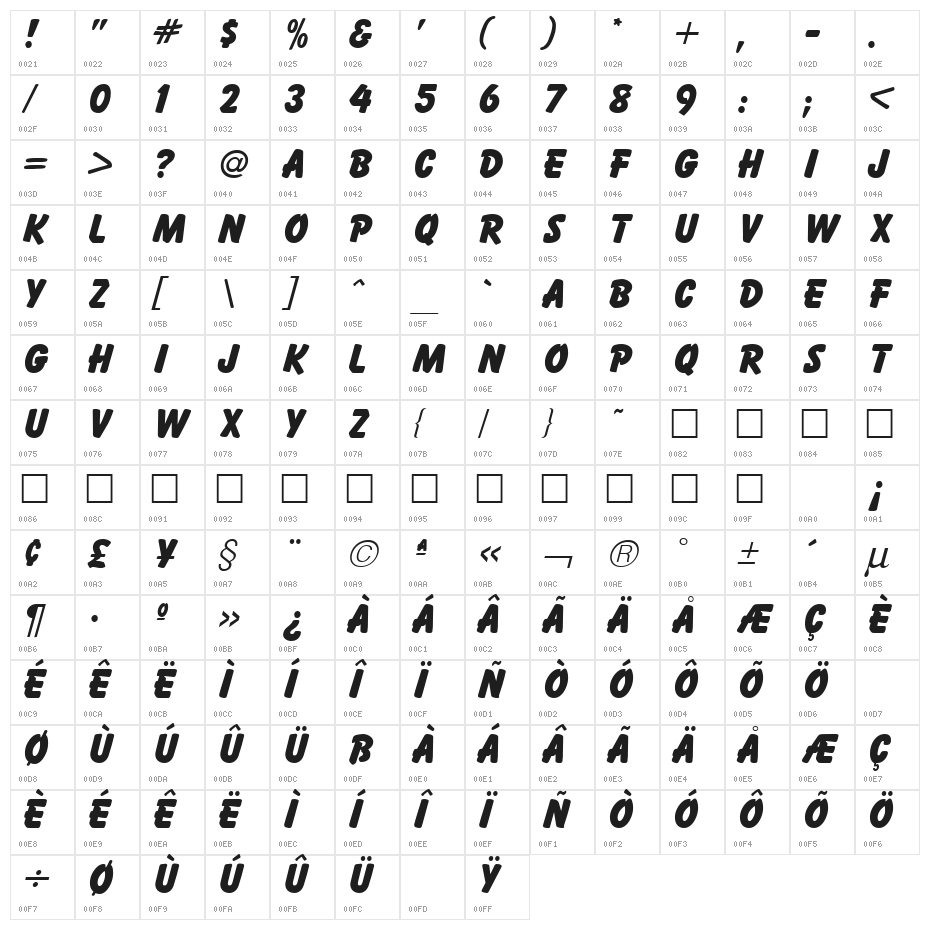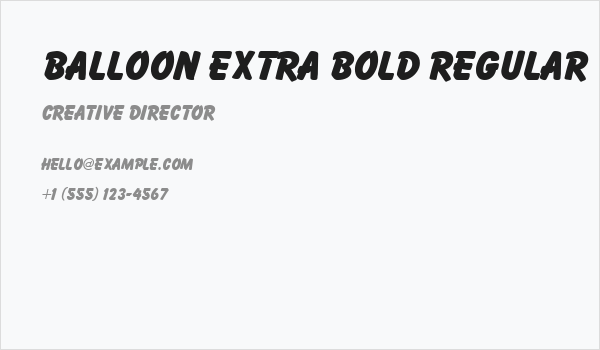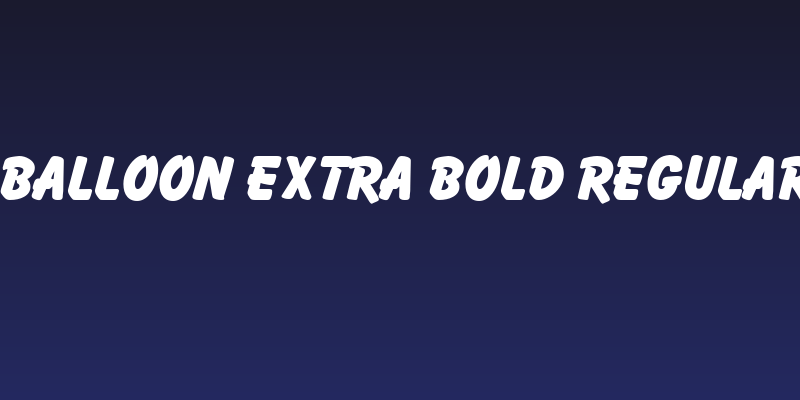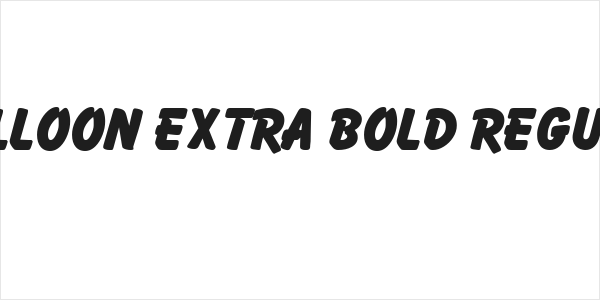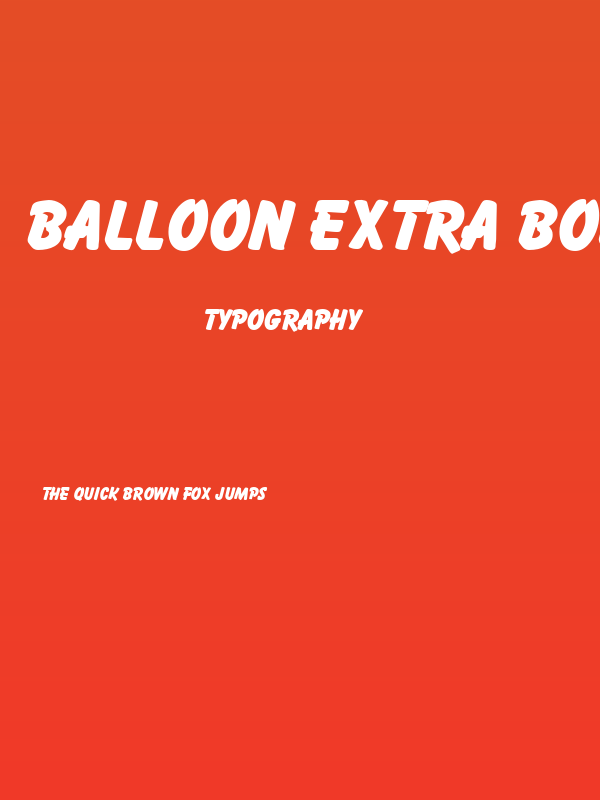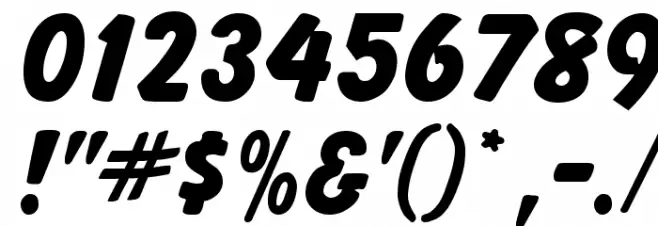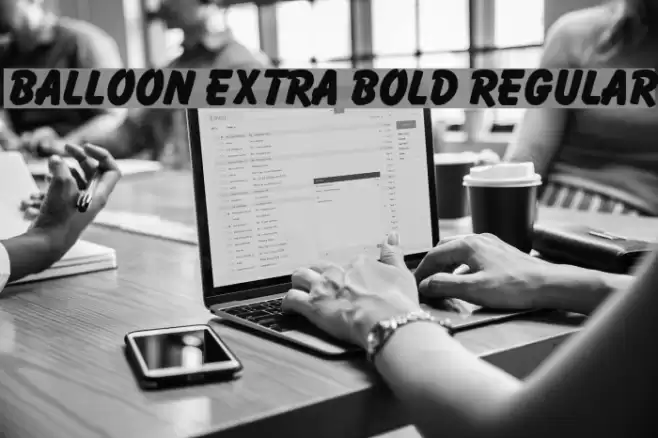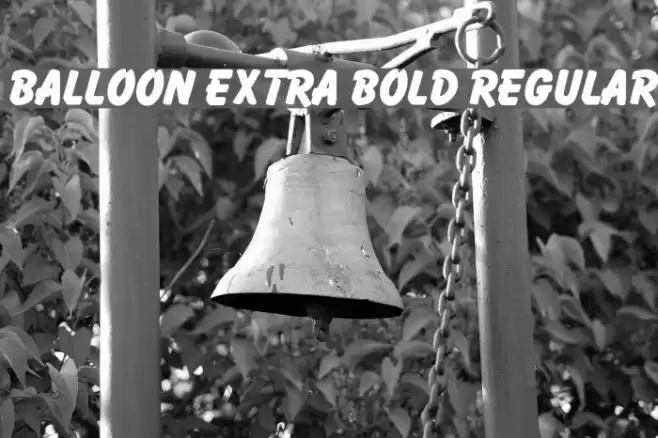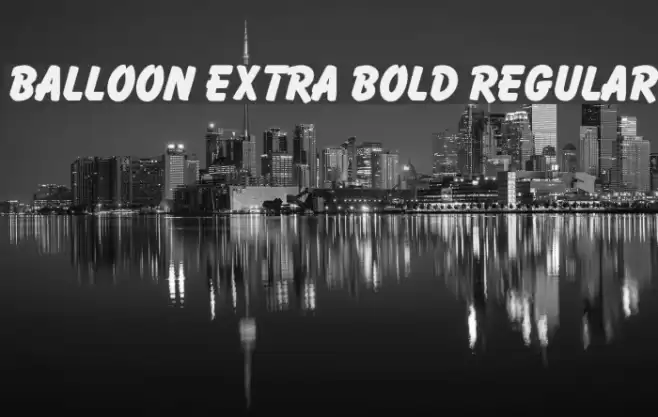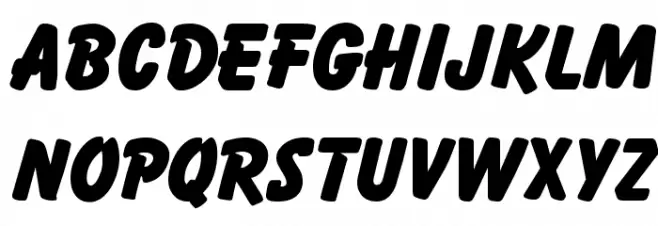
Balloon Extra Bold Regular Font
| समग्र शैली | Playful, Energetic, Fun |
| उपयोग का मामला | Headlines, Logos, Posters |
| सुझाए गए प्रोजेक्ट | Ideal for children's book covers, party invitations, playful branding, and eye-catching headlines. |